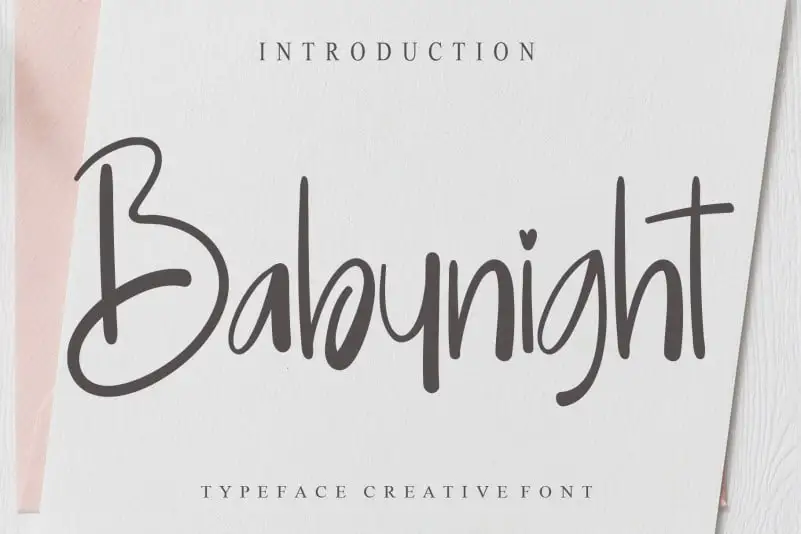
Babynight Script Font – Fonte Grátis
Babynight Script Font
A fonte ‘Babynight Script Font’ é uma criação elegante do designer creativeletter, ideal para quem busca uma fonte escrita a mão para seus projetos digitais. Ela se destaca por sua graça natural e delicadeza, criando um ar suave e acolhedor que encaixa-se perfeitamente em designs de cartões de aniversário, mensagens personalizadas ou até mesmo gráficos infantis. Com seu estilo retrô encantador, Babynight Script Font oferece uma experiência visual única, tornando-a uma escolha inteligente para qualquer projeto que deseja transmitir um toque pessoal e único. Seu design natural e fluido é perfeito tanto para letras grandes quanto para menores detalhes de texto, mantendo a simetria perfeita em cada linha escrita. Para aqueles que buscam algo mais além da estética, Babynight Script Font também promove uma sensação de conforto visual, criando um ambiente acolhedor e suave. Este é o tipo de fonte que parece não ter sido feita para a web, mas sim para imprimir em papel, oferecendo um toque especial a seus projetos digitais. Essa fonte é perfeita para designers gráficos amadores e profissionais que buscam uma maneira única de tornar suas criações ainda mais personalizadas. Seja em cartões de aniversário ou em logotipos, Babynight Script Font oferece um toque especial a qualquer projeto.